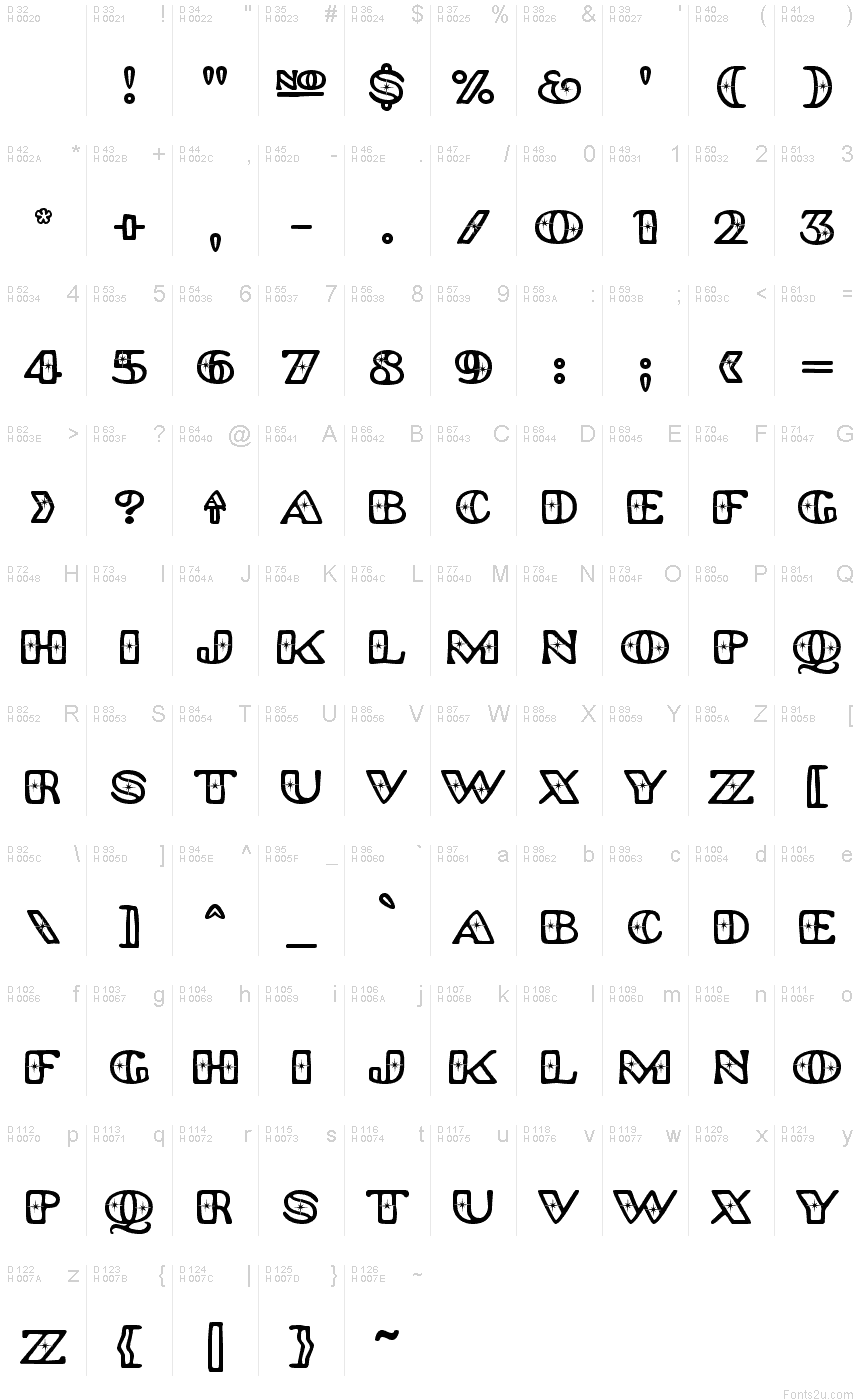
Platinum Hub Caps Polished
Platinum Hub Caps Polished od R. Gasta z GreyWolf WebWorks to darmowy, chromowany krój pisma typu display, utrzymany w klimacie aut customowych. Litery są masywne i zaokrąglone niczym wypolerowane metalowe emblematy, a małe gwiazdki wycięte w liniach nadają alfabetowi salonowego blasku i zabawnego charakteru rodem z końca lat 90.
Świetnie sprawdzi się na ulotkach warsztatów, w logotypach hot rod, menu barów, na okładkach płyt w stylu retro czy planszach tytułowych, gdzie darmowy font z wbudowanym blaskiem błyskawicznie buduje klimat. Sięgnij po niego, gdy zależy Ci na efekcie metalicznej, kolekcjonerskiej powłoki, a nie tylko na pogrubieniu – szczególnie w krótkich nagłówkach, monogramach i napisach na okładkach.